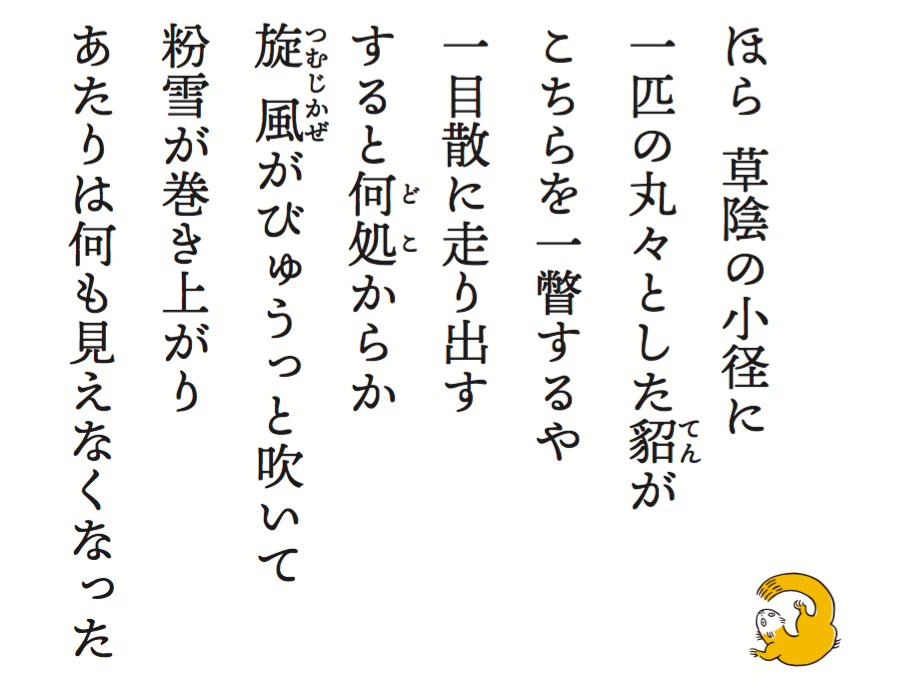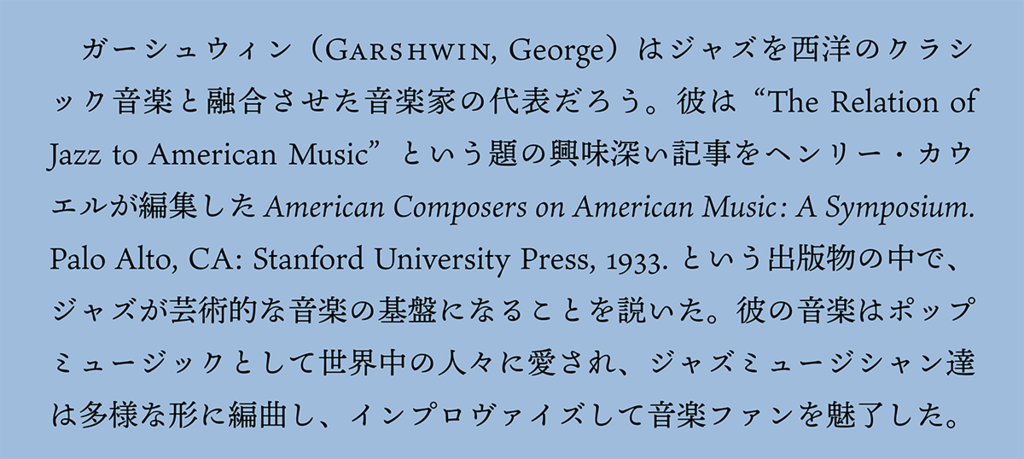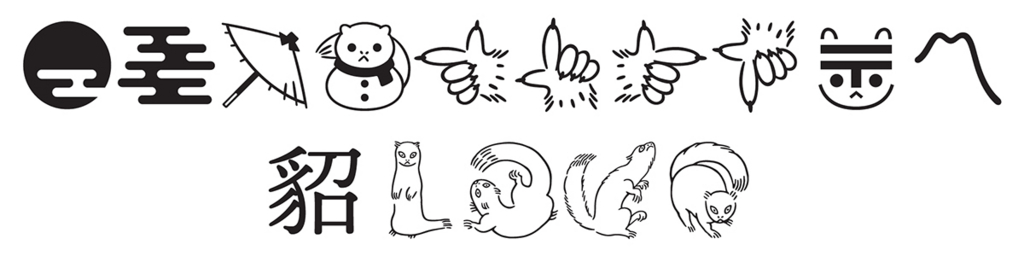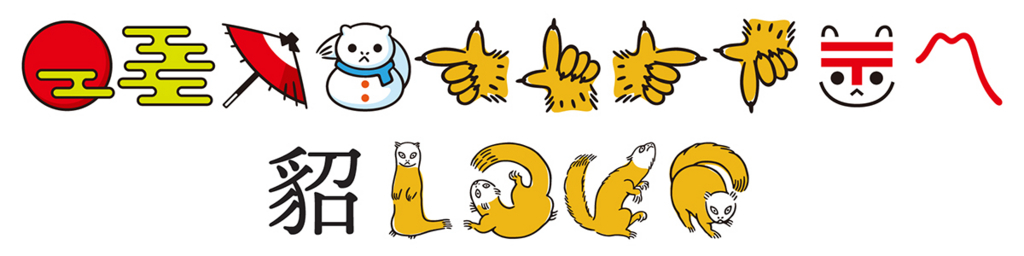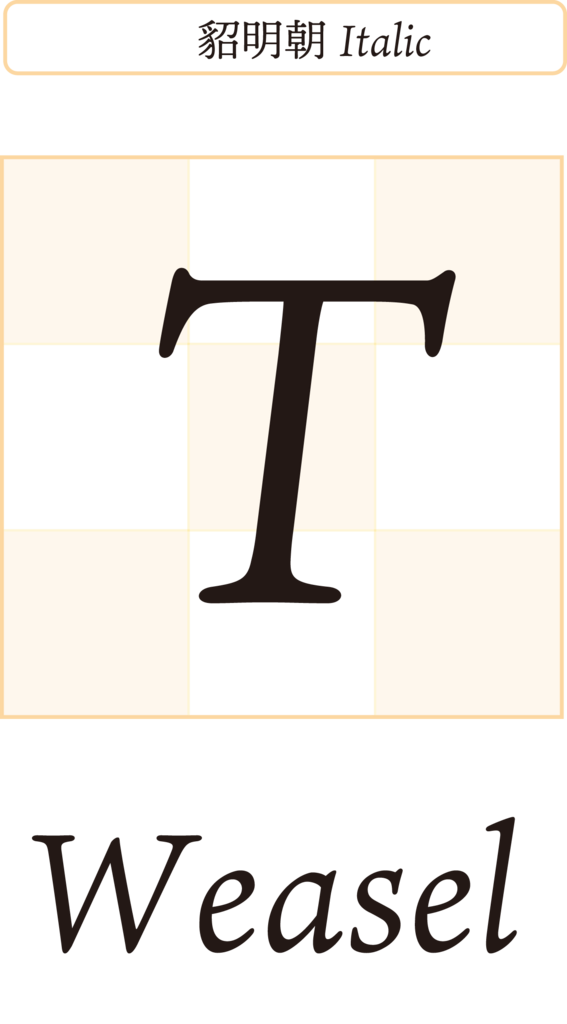
貂明朝
「貂明朝」は、アドビシステムズのチーフタイプデザイナーである西塚涼子氏のデザインによるアドビのオリジナル和文書体となる。
貂明朝の特徴
貂明朝の特徴として躍動感にあふれた手書きの文字に江戸時代の瓦版印刷に見える運筆の特徴も取り入れている。伝統的な明朝体の画線の先端を丸め、やや太めに仕上げ、ふところは小さめにしている。広告コピー、書籍・出版物のタイトルなど幅広い用途で使用できる。
書体はJIS X 0208の第一水準と第二水準の漢字、最新の常用漢字と人名用漢字の文字集合を含む6,469文字を収録。独自の特徴として符号化されていない異体字形を含まないことや、それがJIS2004基準であること、ディスプレイ書体でありグリフはJIS90基準の形よりJIS2004基準の形により近いといった特徴を有している。
貂明朝にはフルセットの欧文グリフも含まれおり、その欧文グリフは Ten Oldstyle という書体名が付けられたもので、アドビのType部門のプリンシパルデザイナー、ロバート・スリムバック氏がデザインした。
手書きのカリグラフィがもつ素早い筆致と、イタリアルネサンスの古典的人文主義様式の本文用活字書体のもつ実用性とを、Ten Oldstyle は兼ね備えている。
貂明朝は貂のキャラクターの異体字がかわいい!
西塚氏が貂明朝開発時にコンセプトを説明するために描いた4種類のキャラクターが社内で人気が出たため、異体字として4種のキャラクターが入力できるようになっているようだ。SVG(Scalable Vector Graphics)のカラーグリフも提供予定とのこと。きつねの〒記号もかわいい。
貂明朝 書体見本
▼貂明朝 Regular
▼貂明朝 Italic